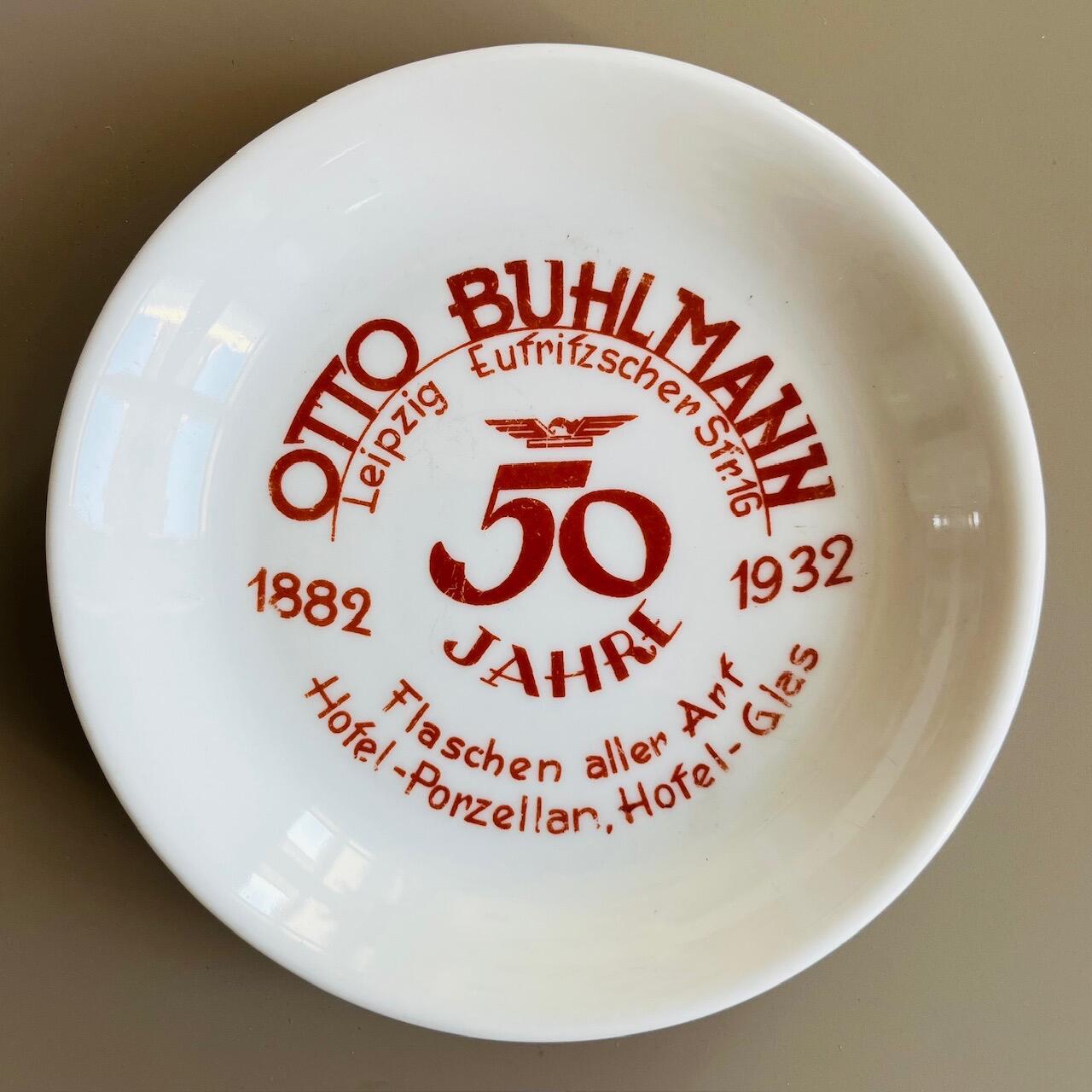
Fast alle Schriftsysteme kennen einen Strichkontrast.
Es ist ja nicht so, dass es keinen Kontrast bei serifenlosen Schriften gäbe ... :-P
würde auch als |f| funktionieren
Wieso "würde"? Funktioniert doch prächtig in der Eufrifzscher Sfr. ...
Wer oder wo auch immer Eufrifzsch war ...
Was'n 'n Hofel und Arf?
Fontkombinationen wissenschaftlich untersucht, hier der/das Abstract der Studie:
In a field traditionally driven by intuition and subjective judgment, this study presents a data-driven approach to typography, the art of arranging text. Leveraging a comprehensive dataset of font-use cases across diverse mediums, we employed Non-negative Matrix Factorization to extract three fundamental morphological characteristics of fonts: Serif vs. Sans-Serif, Basic vs. Decorative letterforms, and Light vs. Bold. This analysis demonstrated that different mediums preferentially utilize fonts with distinct morphological features. We also predicted variations between single and paired fonts, contrasting these findings with random pairings from several null models, to identify unique font-pairing trends across various mediums. Furthermore, we utilized a network analysis approach to identify the most authentic font pairings, thereby yielding practical insights for typography applications. The primary contribution of our research lies in significantly enhancing the understanding of typographies. Our work lays the groundwork for the scientific exploration of the systematic categorization of fonts and their pairings. This study establishes foundational principles for the application of typography in visual communication.